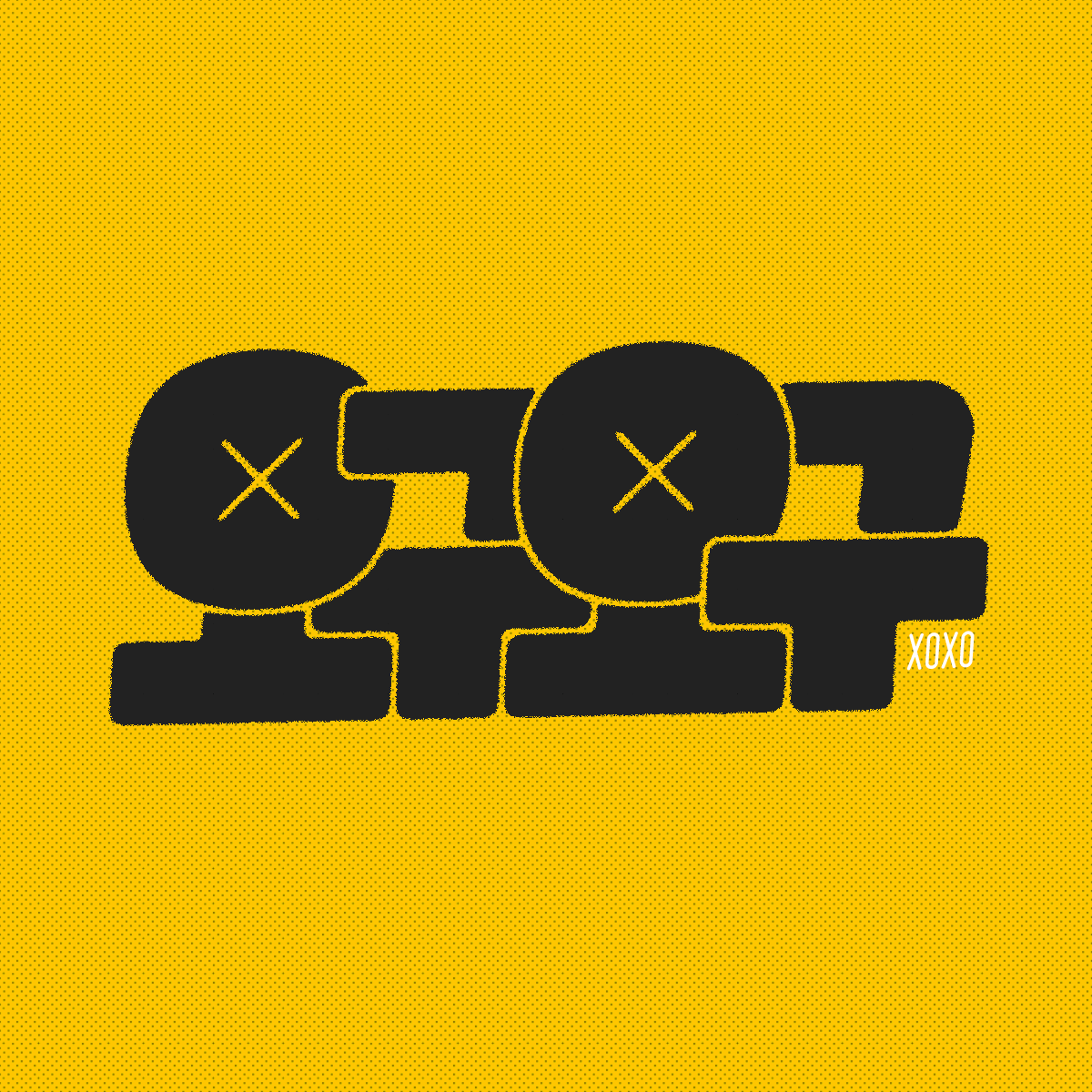
오구오구 / XOXO
ZESSTYPE LETTERING WORK 2017
특정 의미를 갖는 짧은 단어를 동일한 표현 방식으로 레터링 작업을 이어가고 있다.
큰 의미를 갖는 작업은 아니지만.
차곡차곡 모아서 이모티콘 같은 형태로 제작하면 어떨까 싶어서 작업하고 있다.
한글을 소재로 상품화하는 시도는 이전부터 계속되어 왔지만.
한글의 우수함이라든지. 뭐 과학적 어쩌고 그런 것보다는.
사람들이 친숙하게. 일상적으로 사용할 수 있는 무언가를 만들고 싶다.
잘 될지는 모르겠지만. 또 언제가 될지는 모르겠지만.